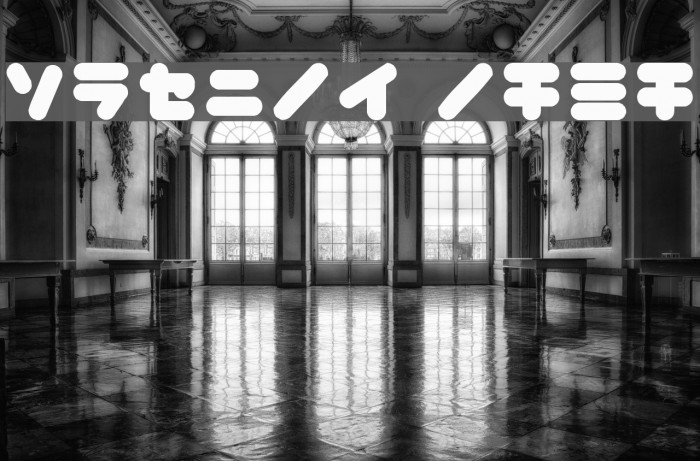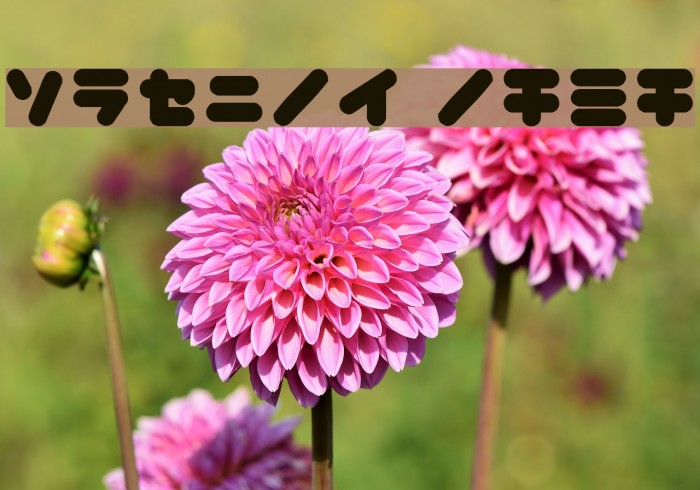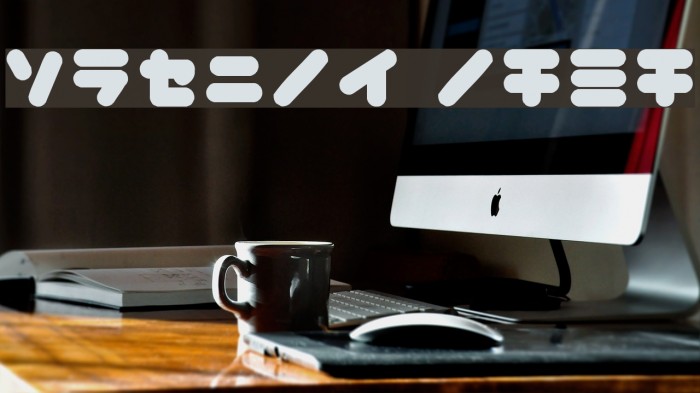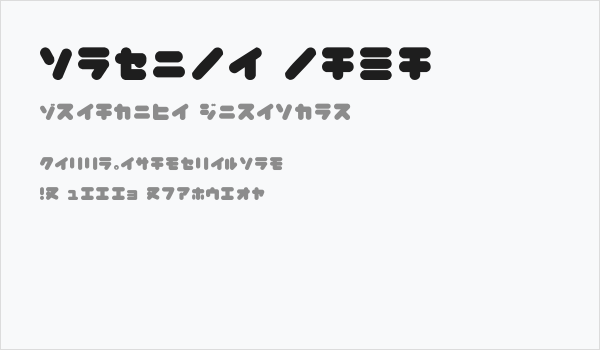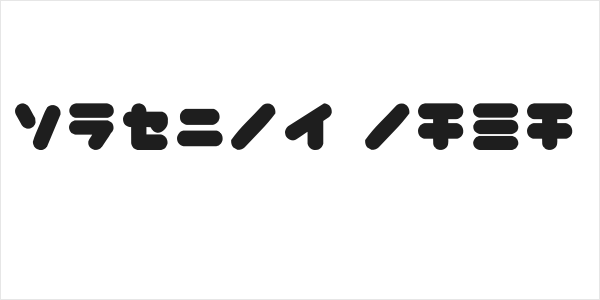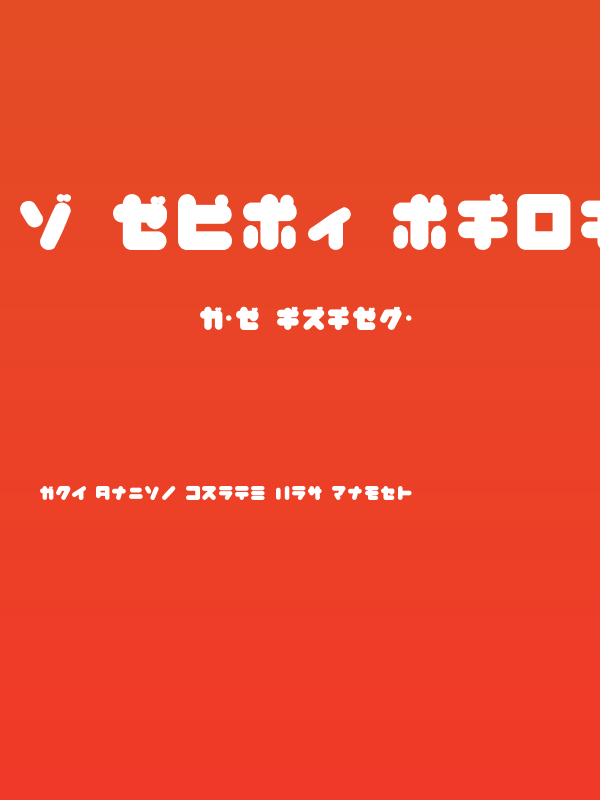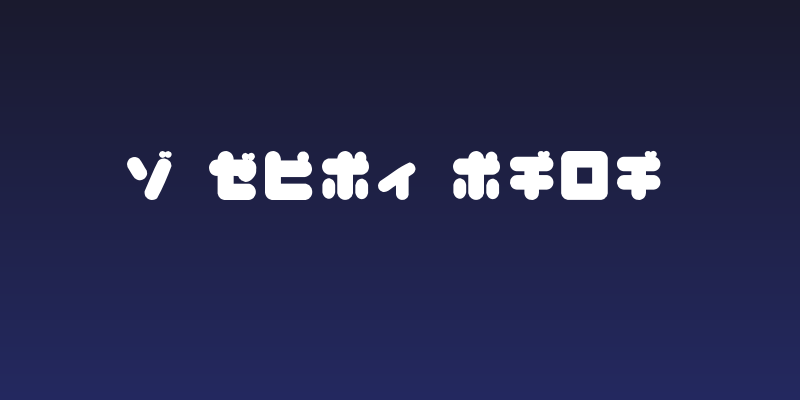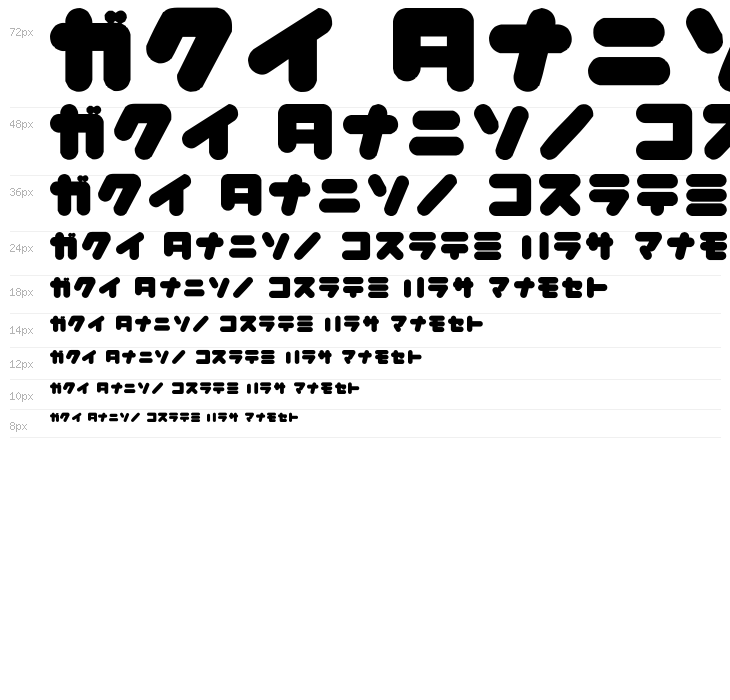
copike kana Font
| Estilo general | Playful, Cartoonish, Fun |
| Caso de uso | Headlines, Posters, Branding |
| Proyectos propuestos | Ideal for children's books, comic strips, playful branding, and informal event posters. |